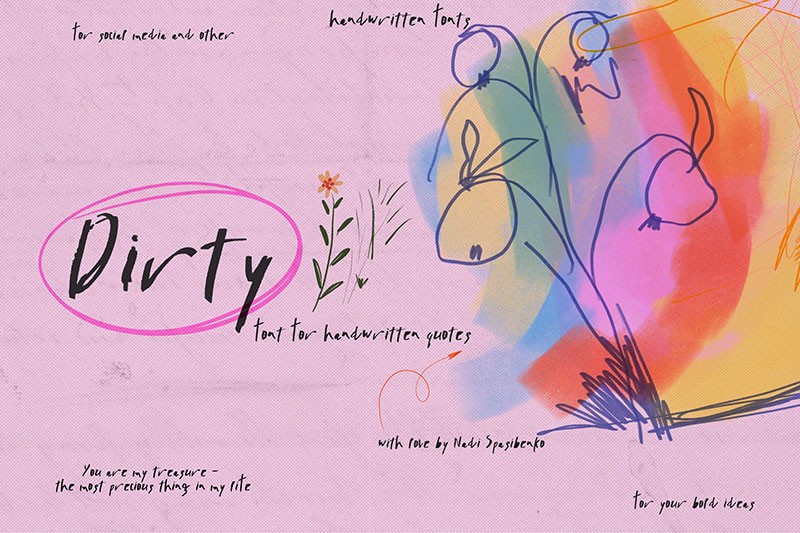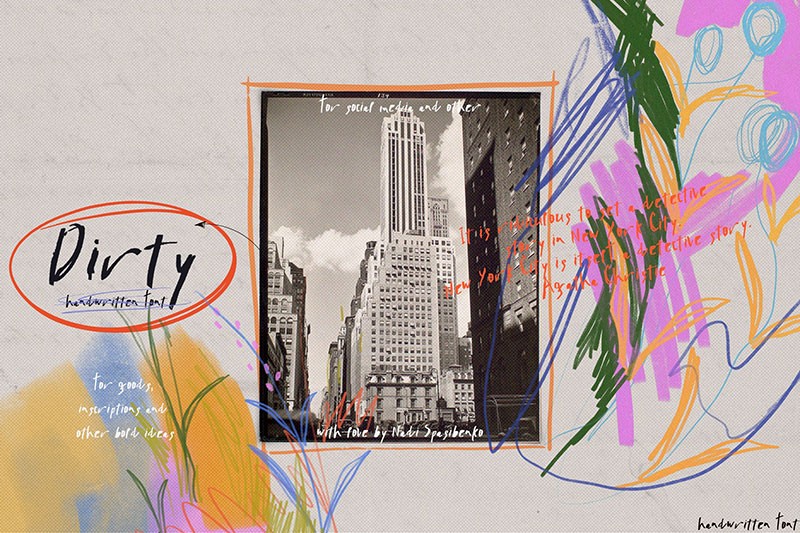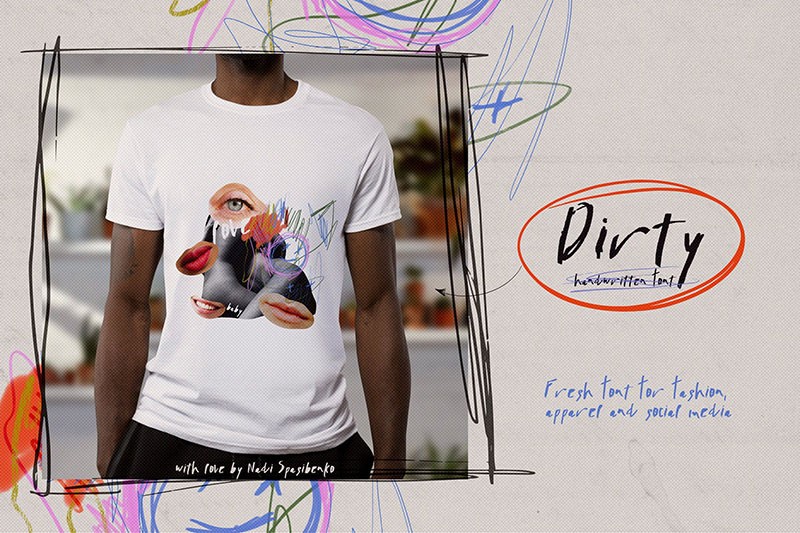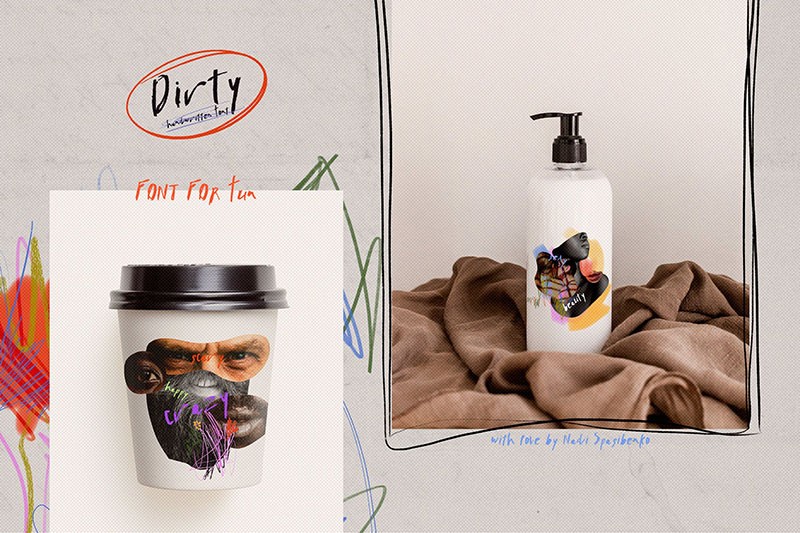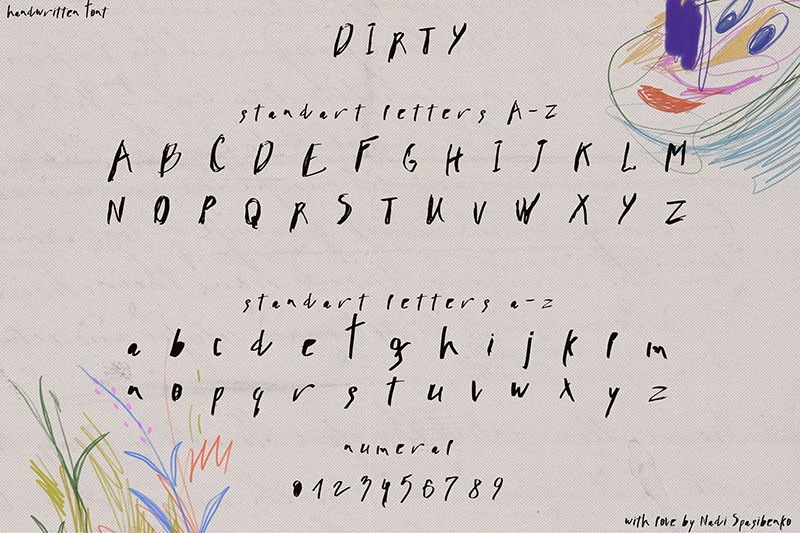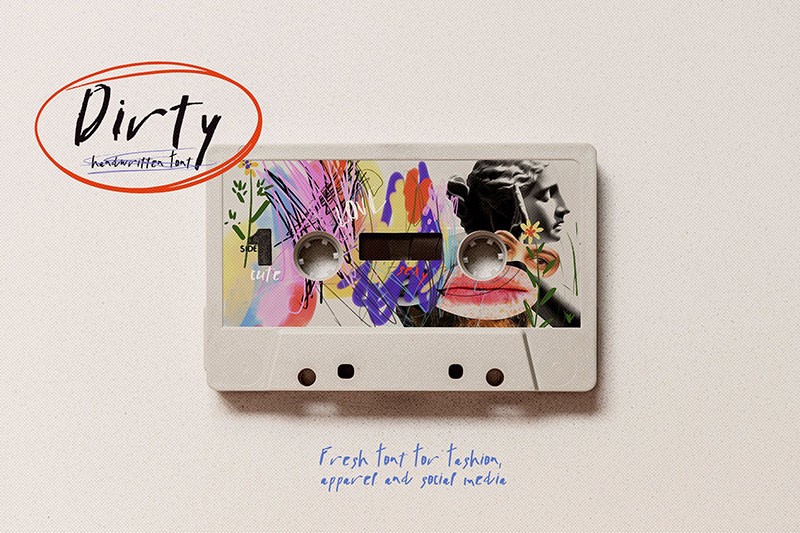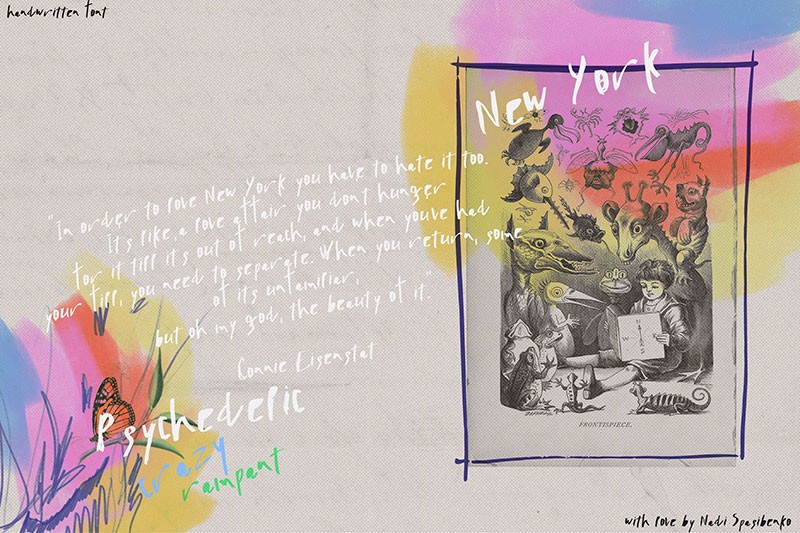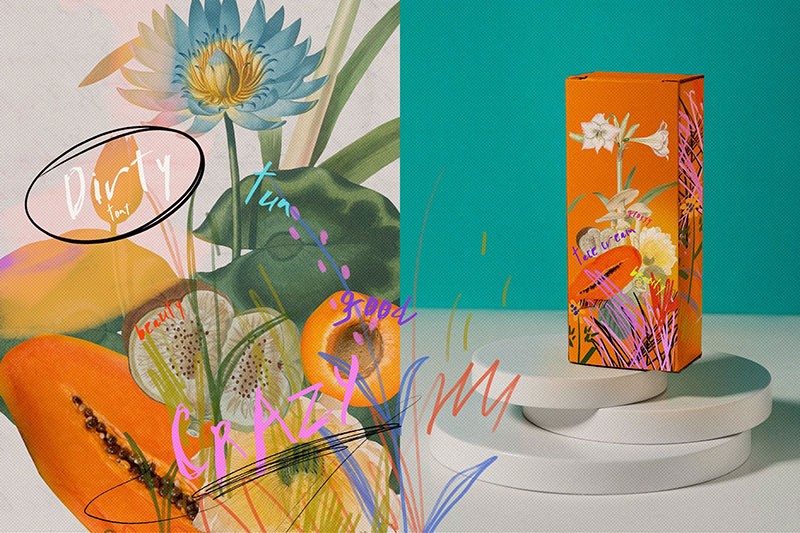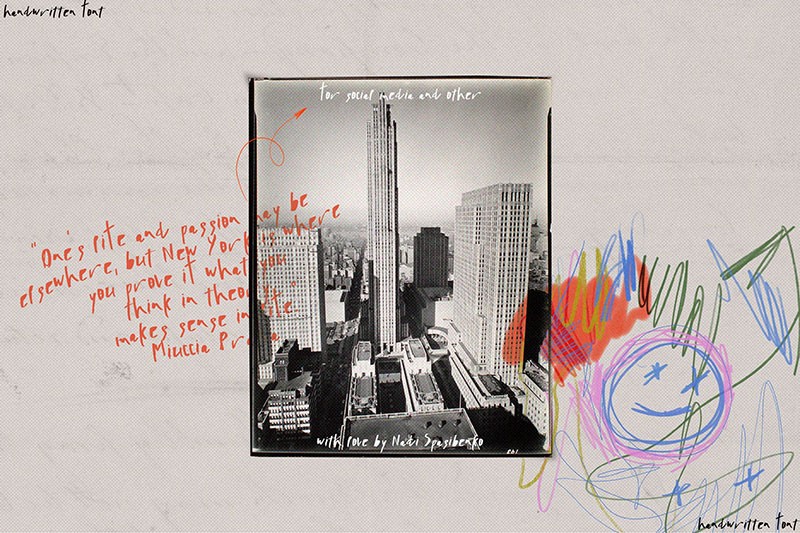
SA Dirty真实感英文签名字体
一款独特的手写风格字体,具有粗糙、脏乱的外观。它的字母形状不规则,线条有时候会断裂或交错,给人一种放荡不羁、叛逆的感觉。SA Dirty字体适用于设计中需要突出个性、表达粗犷或另类风格的场合。它可以为你的作品、海报、标志、音乐封面等带来一种独特的视觉效果,让你的设计脱颖而出。